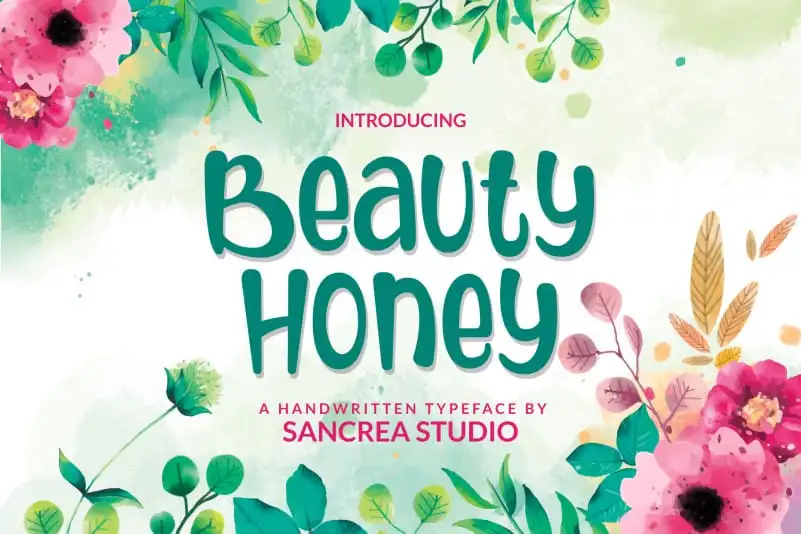
Beauty Honey Script Font – Download Grátis
Introduzimos a Beauty Honey Script Font. Esta tipografia é uma fonte escrita à mão com letras grandes e engraçadas. Ela é uma fonte em maiúsculas. Ideal para citações, cabeças de página, blogs, logotipos, convites e muito mais! Perfect para usar em projetos digitais e impressos que exigem um toque delicado e original, a Beauty Honey Script Font encaixa-se perfeitamente nessas necessidades. Seja você um designer ou criador de conteúdo online, ter uma fonte desta qualidade na sua gaveta pode tornar o seu trabalho mais atraente e único.